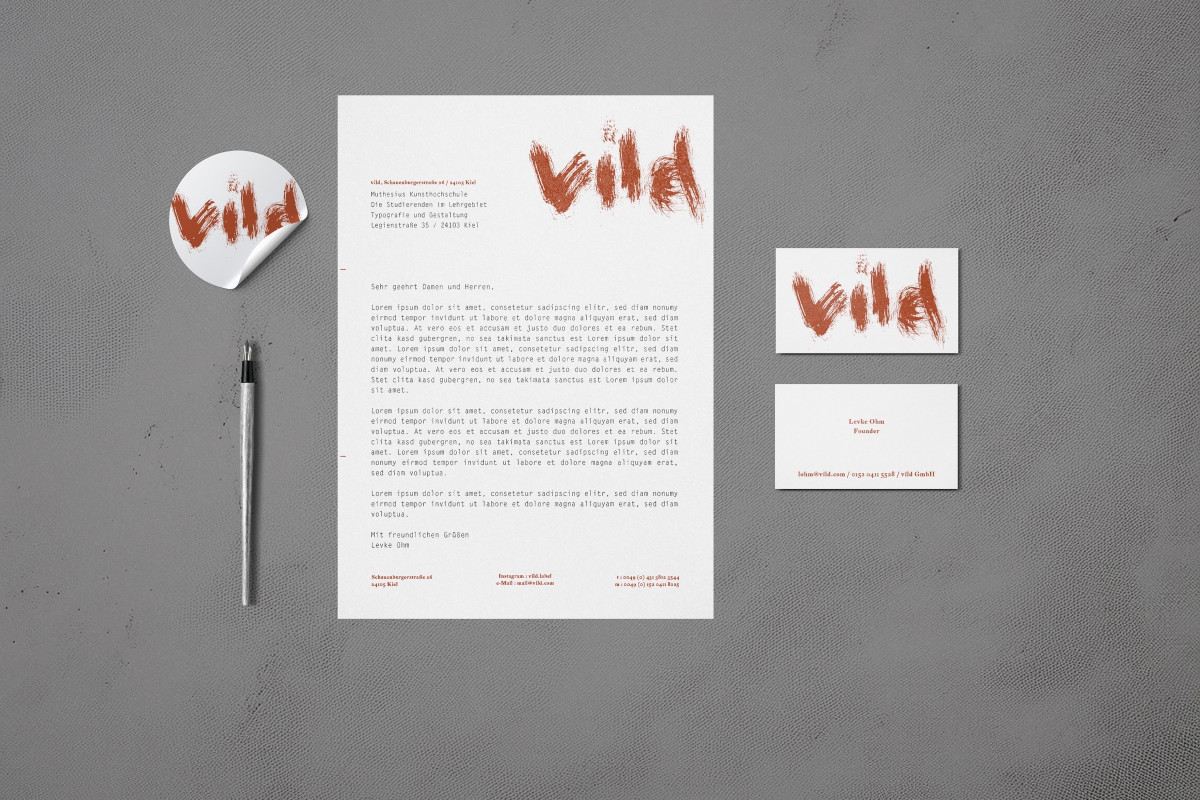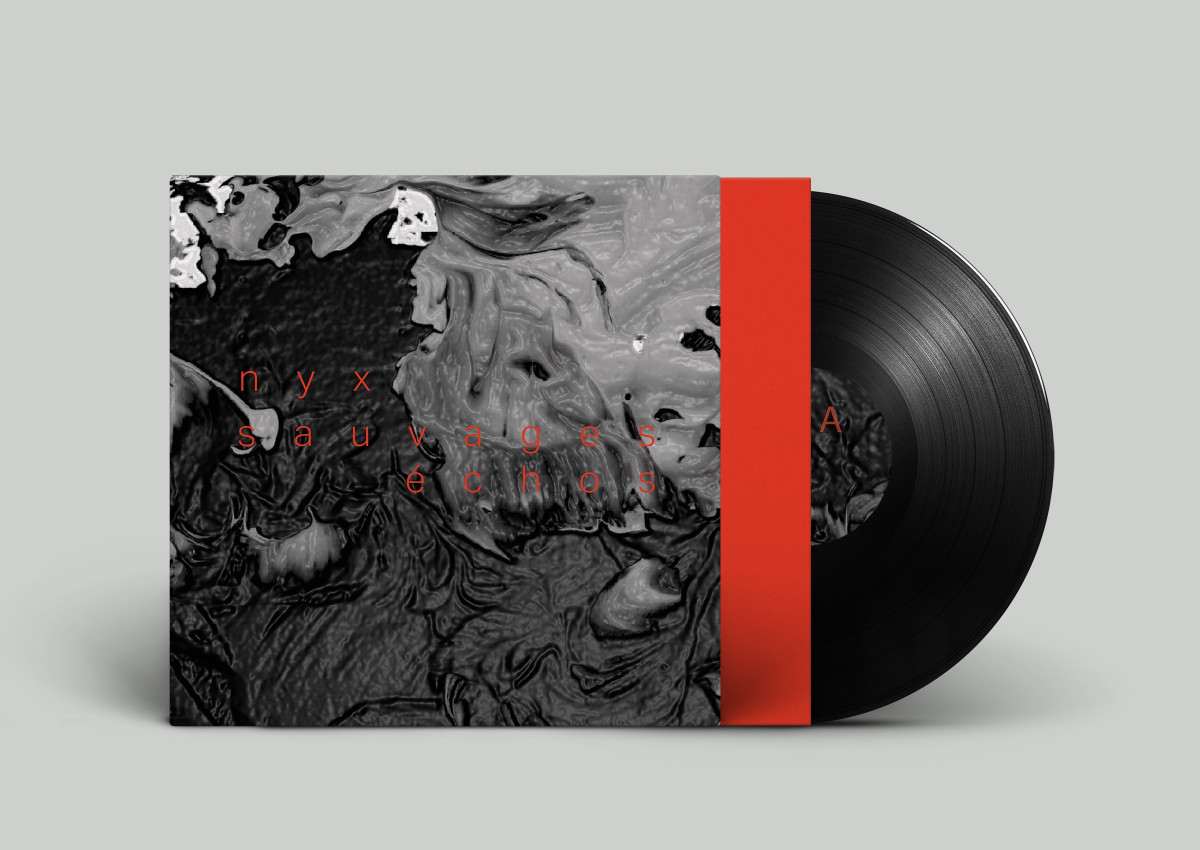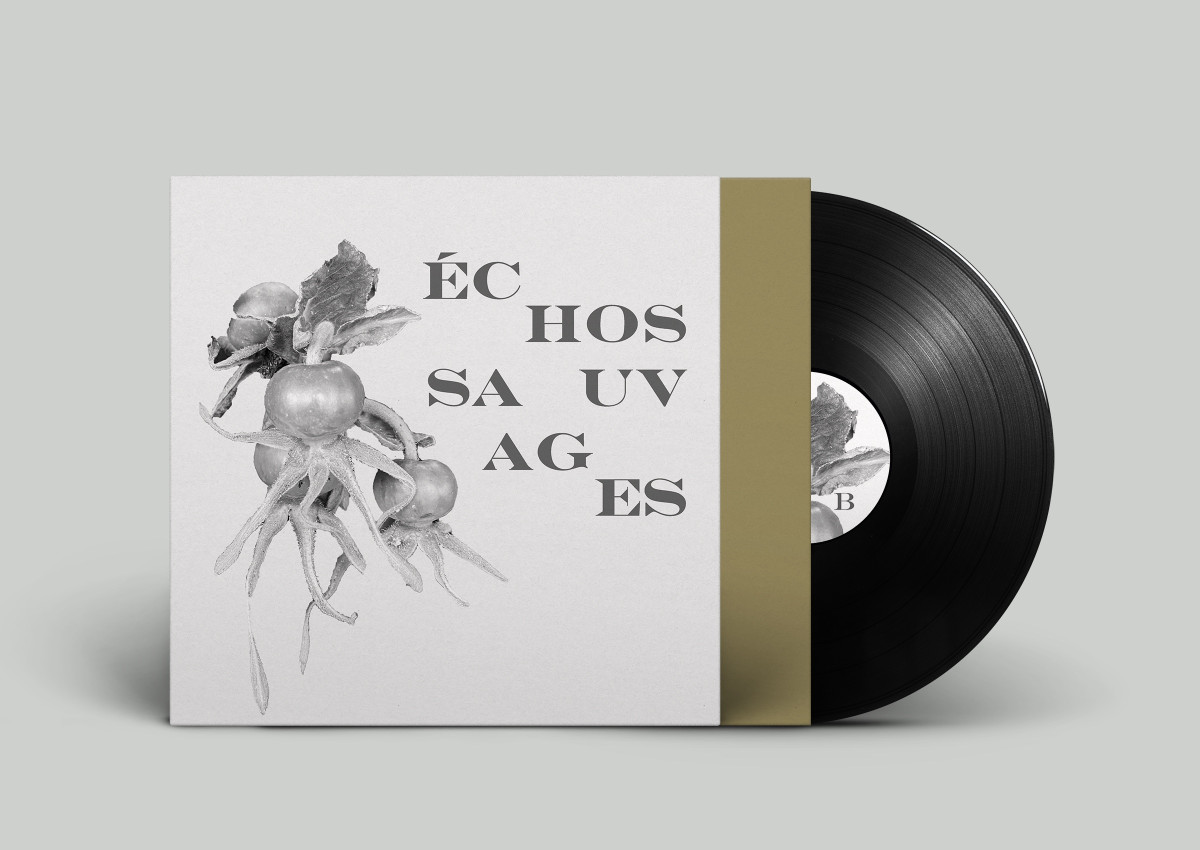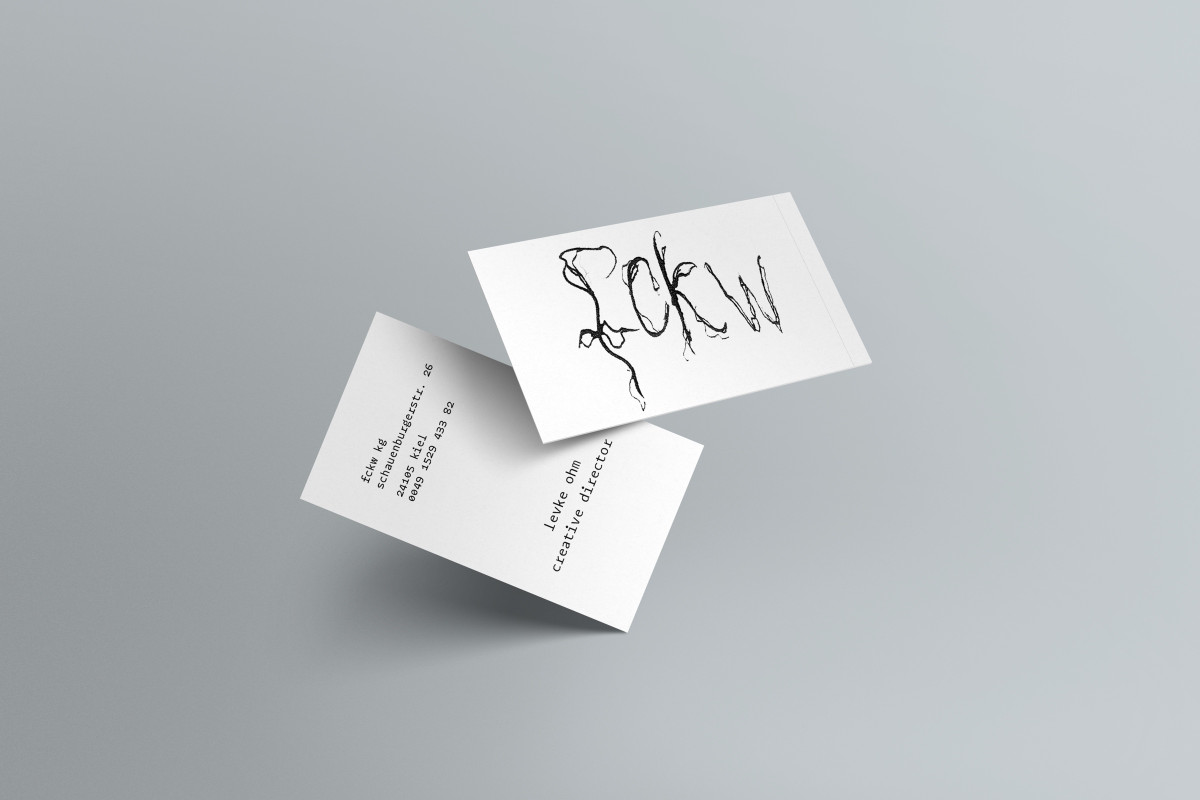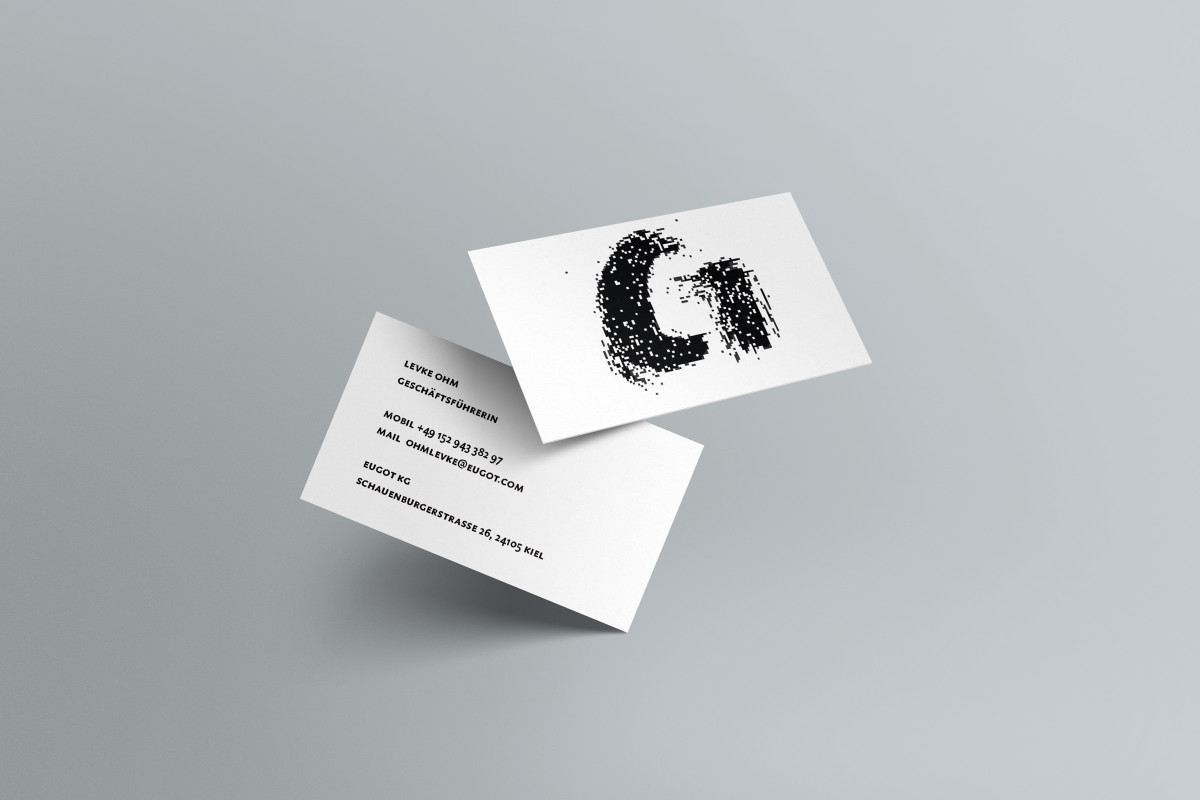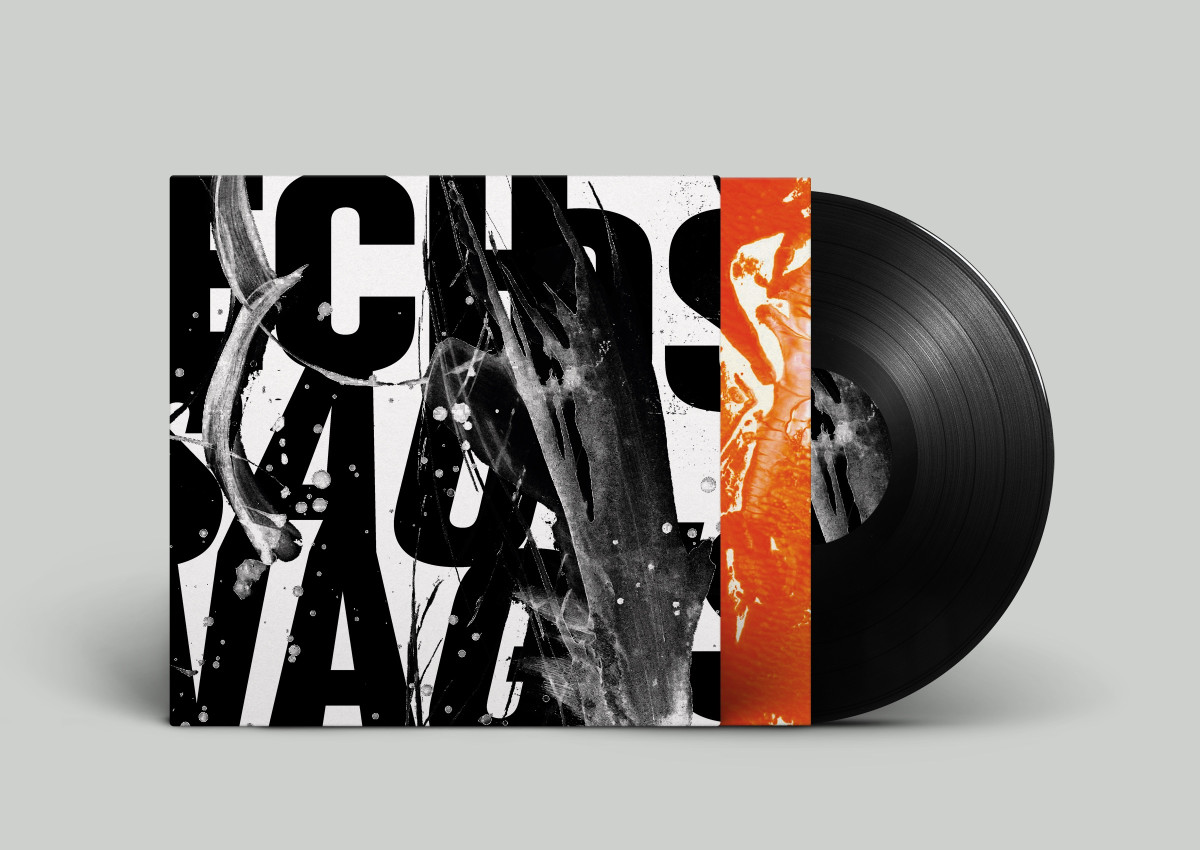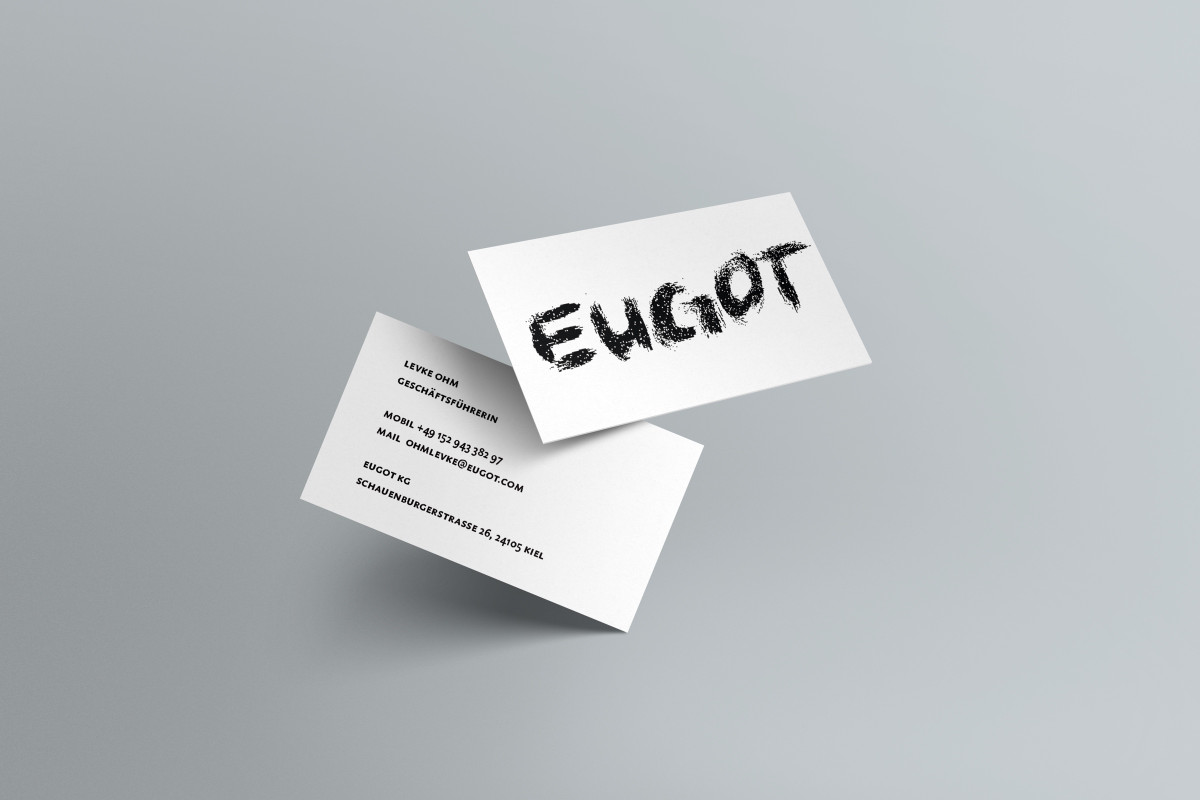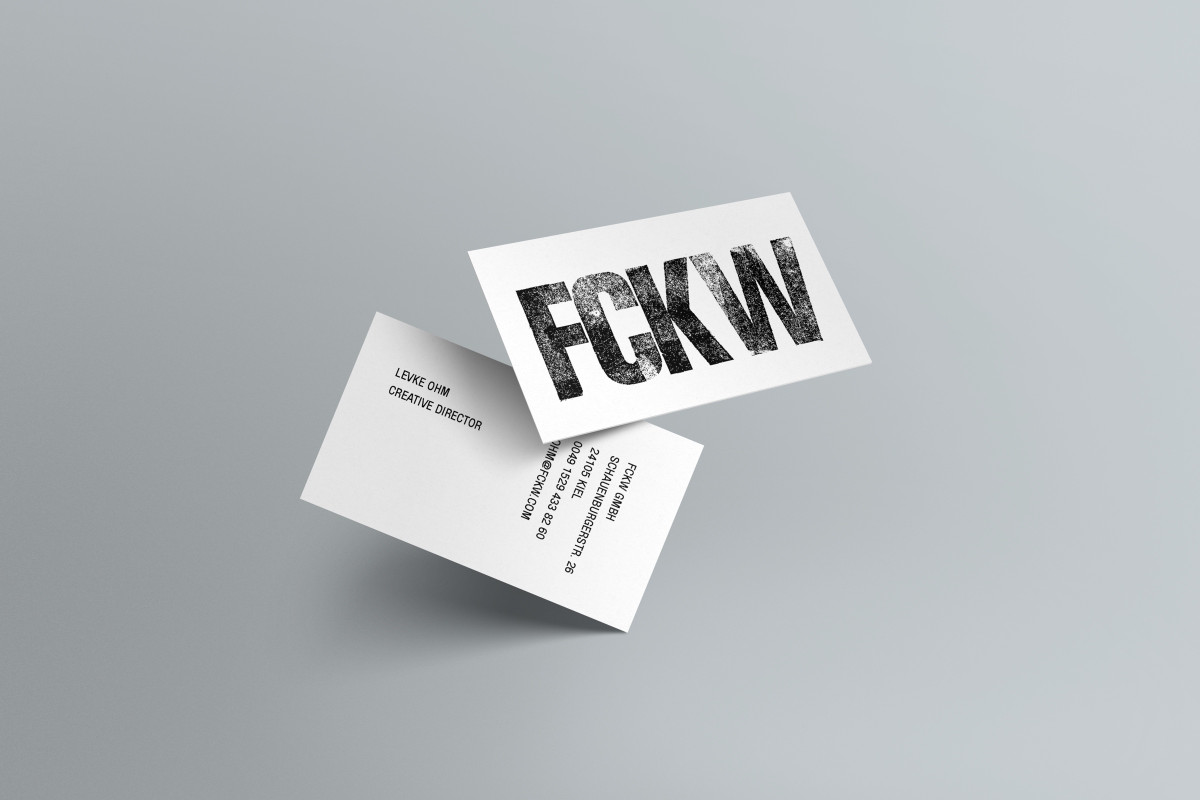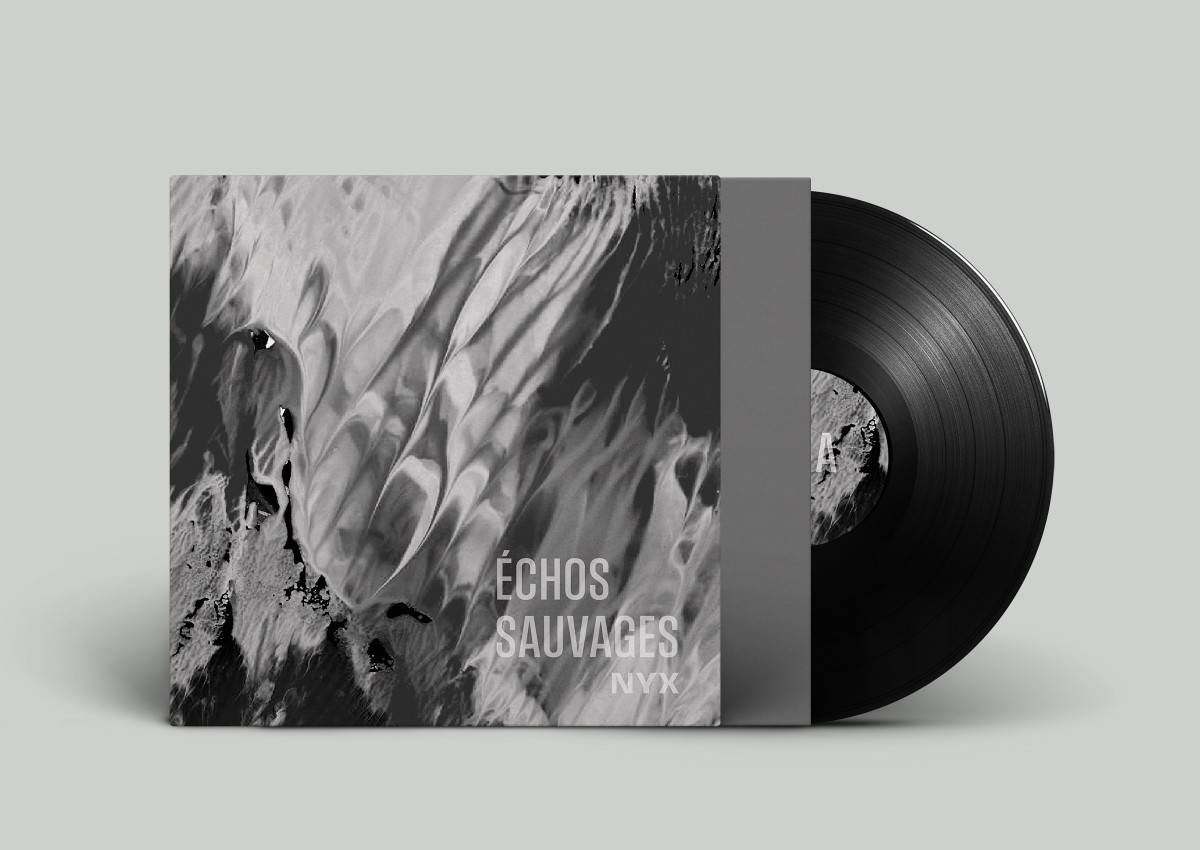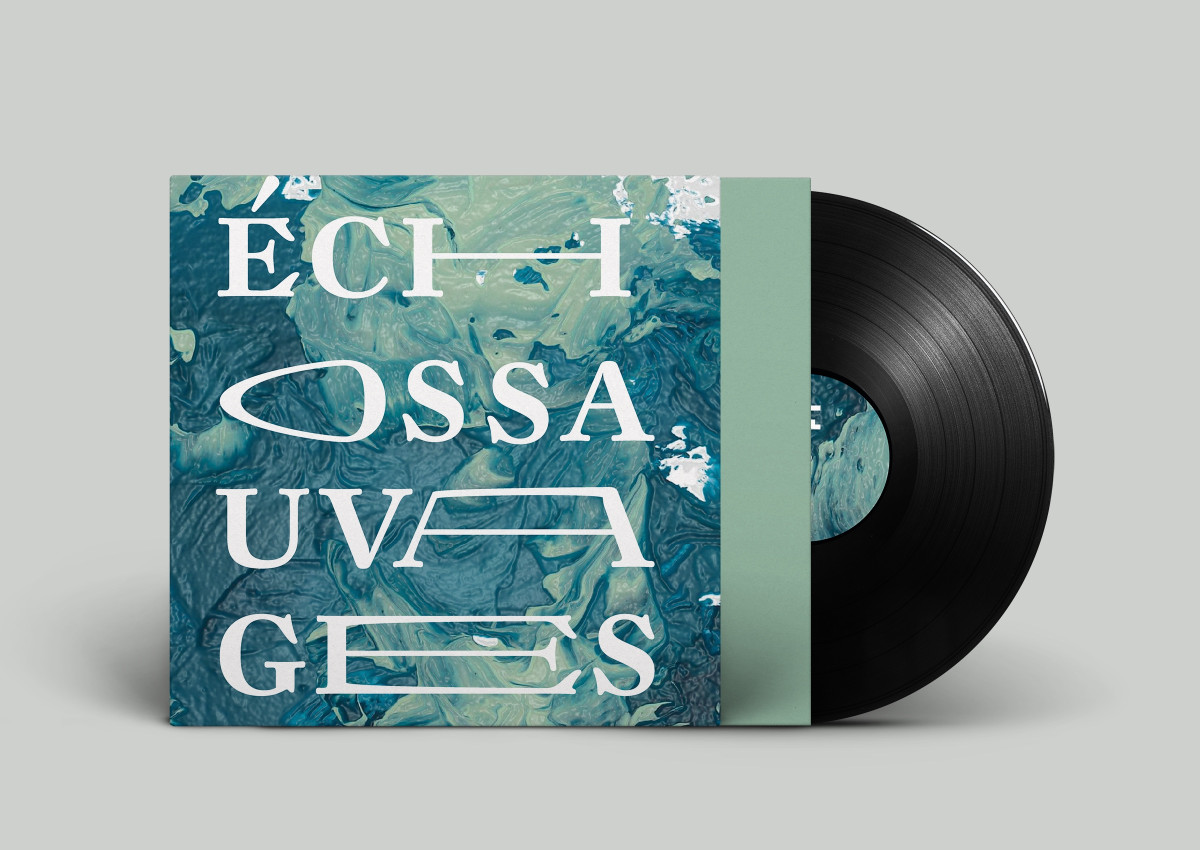
Im Wintersemester 2024/25 entwickelten wir ein grafisches Erscheinungsbild für ein Plattenlabel, das sich auf Free Jazz und experimentelle Musik spezialisiert hat.
In meinem Gestaltungsprozess arbeitete ich zunächst analog mit verschiedenen Techniken wie Bleisatz, Pinsel, Feder und Filzstiften. Bei der Wortfindung ließen mich Fachbegriffe, Übersetzungen und selbst kreierte Wortschöpfungen inspirieren.
Das Ergebnis war eine vielfältige Auswahl an Logos, Visitenkarten und Geschäftsausstattung. Während des Prozesses gelang es mir, den verschiedenen Erscheinungsbildern jeweils eine eigene Ausstrahlung und Charakteristik zu verleihen.
Zum Abschluss des Semesters gestalteten wir auch Plattencover. Hierfür erstellte ich zunächst analoge, abstrakte Strukturen mit Acrylfarbe und Tinte, die ich anschließend digitalisierte und in Photoshop weiter bearbeitete. Ein besonderes Highlight war die eigenhändige Herstellung der Plattencover.
In the winter semester of 2024/25, we developed a visual identity for a record label specializing in free jazz and experimental music.
The overarching theme of "the wild" could be freely interpreted whether through design, contrasts between typography and illustrations, or in relation to nature. In my design process, I first worked analogously with various techniques such as letterpress, brush, pen, and felt-tip markers. During the word-finding process, I drew inspiration from technical terms, translations, and self-created word inventions.
The result was a diverse selection of logos, business cards, and corporate design materials. During the process, I succeeded in giving each of the visual identities its own unique presence and characteristics.
At the end of the semester, we also designed record covers. For this, I first created analog, abstract structures using acrylic paint and ink, which I then digitized and further edited in Photoshop.